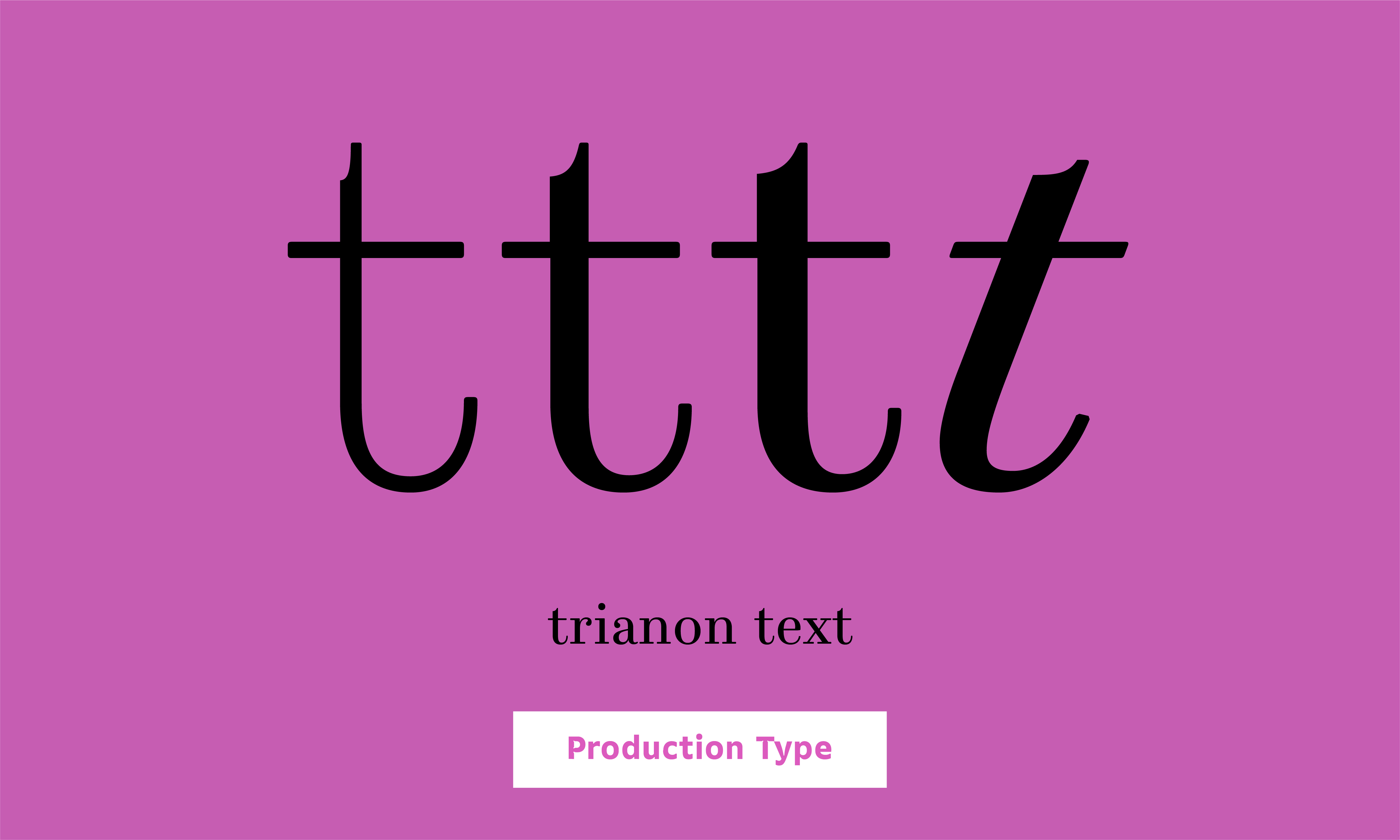
- Trianon은 패션잡지나 명품브랜드에서 자주 사용하는 Didot과 유사하지만 화려한 장식보다는 리듬과 가독성 등에 보다 집중한 폰트이다.
Trinon Caption과 Text는 특히 작은 글자들이 길게 타이핑 되었을 때를 위해 튼튼한 인상으로 디자인 되었다.
폰트 정보 폰트명 Trianon Text 구분 명조 폰트디자인 Loïc Sander, Sandra Carrera, Roxane Gataud, Yoann Minet